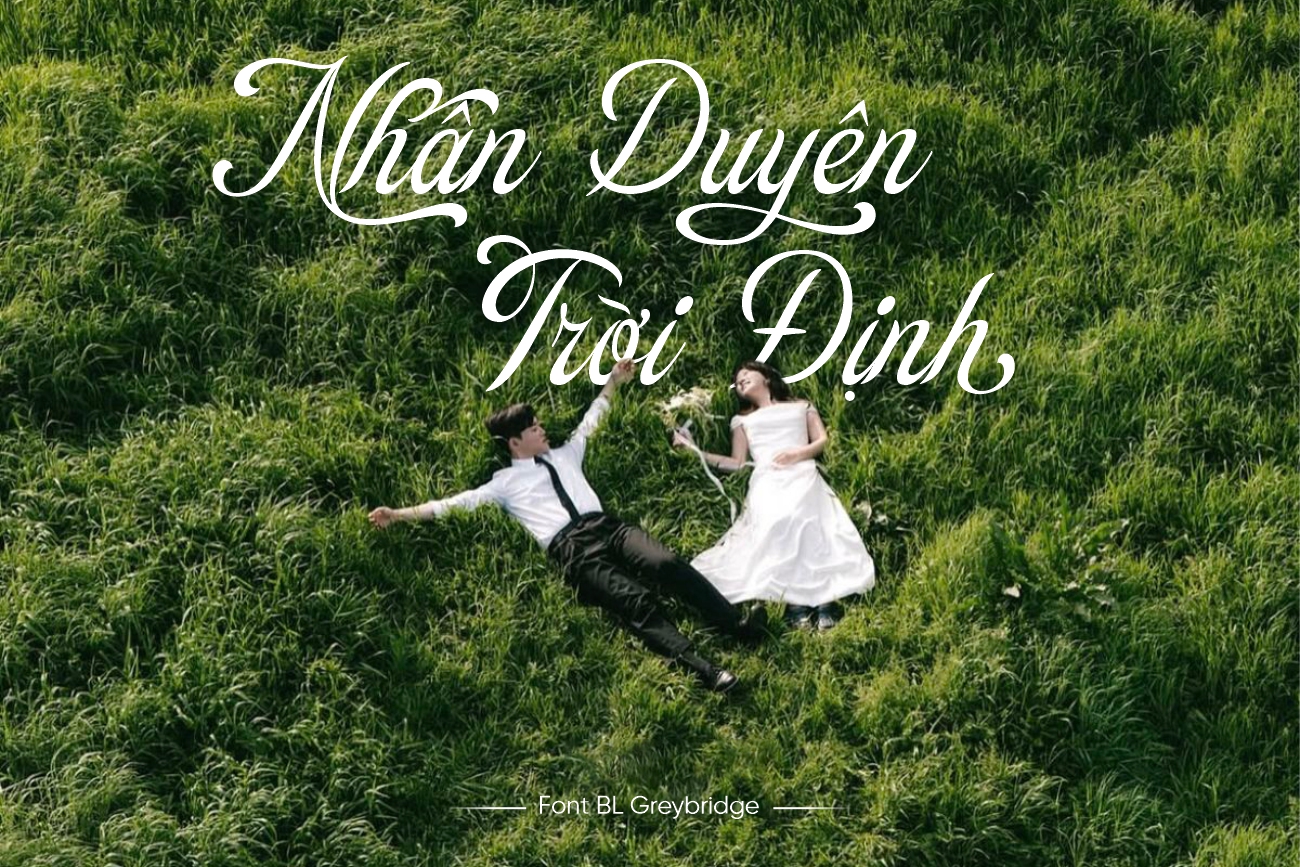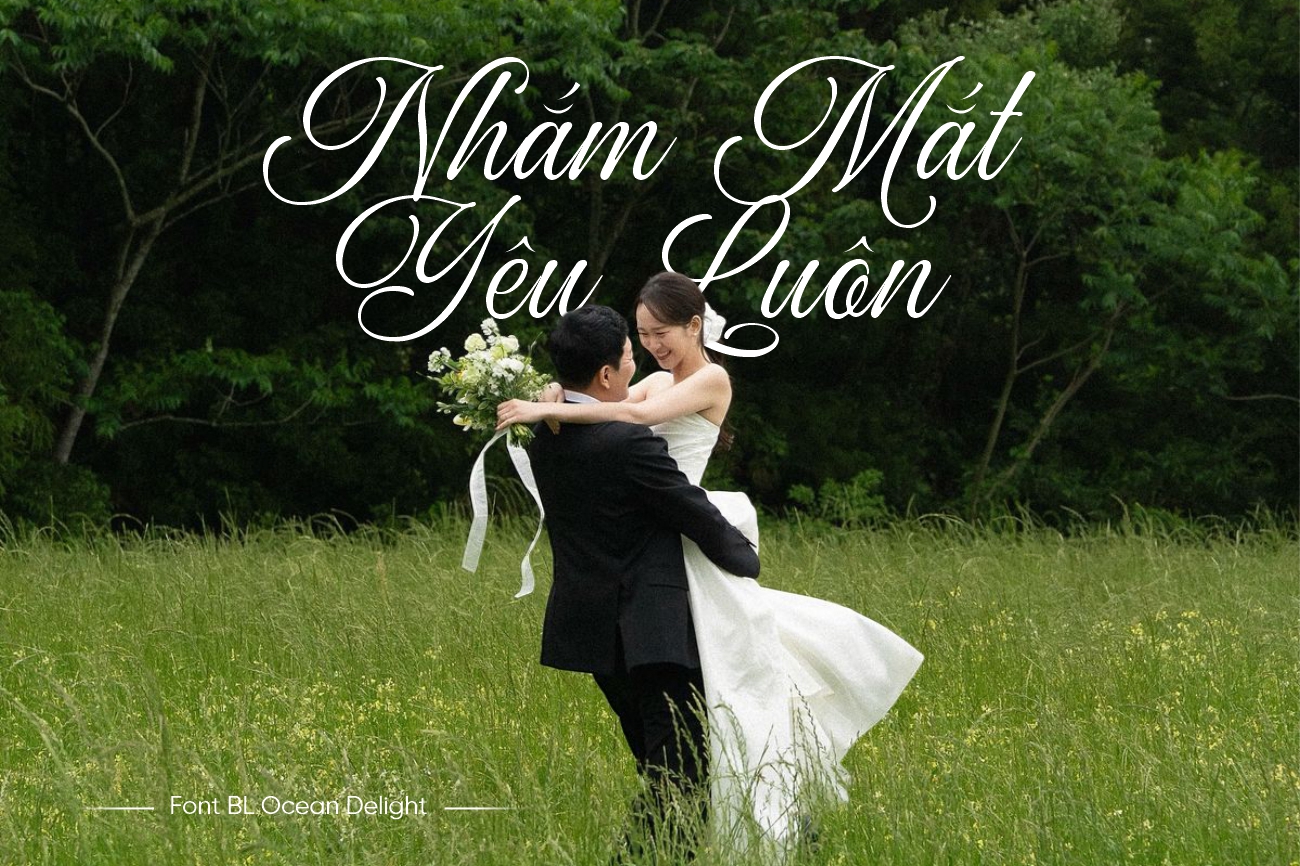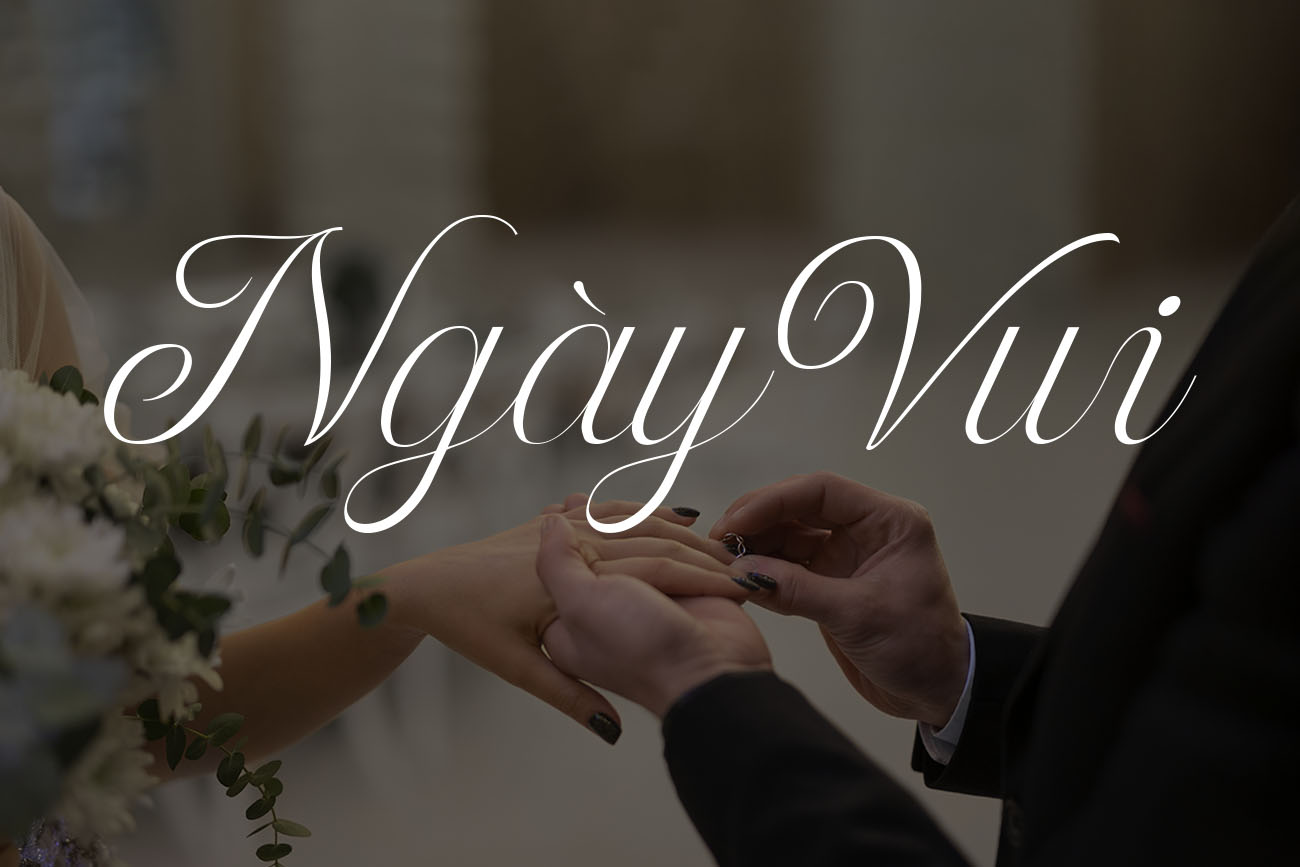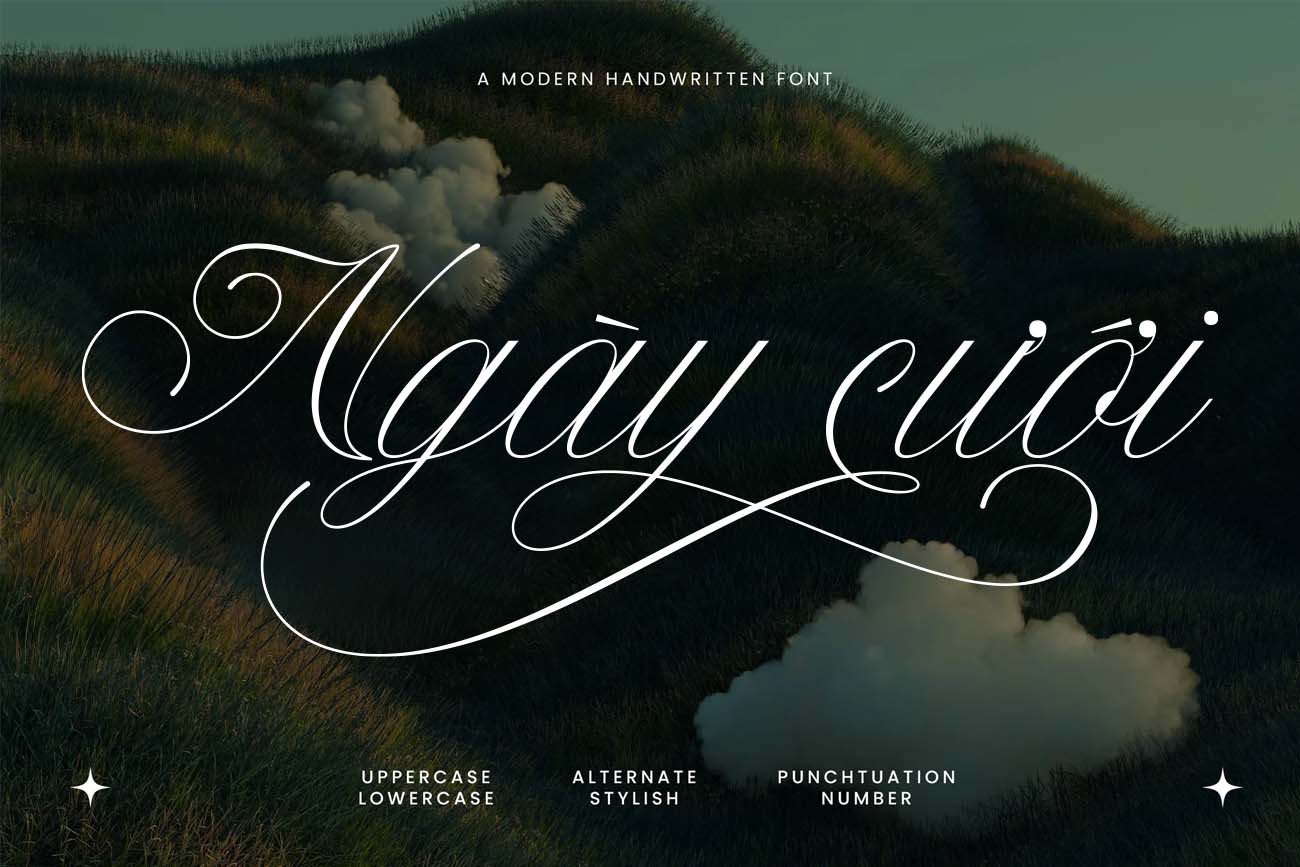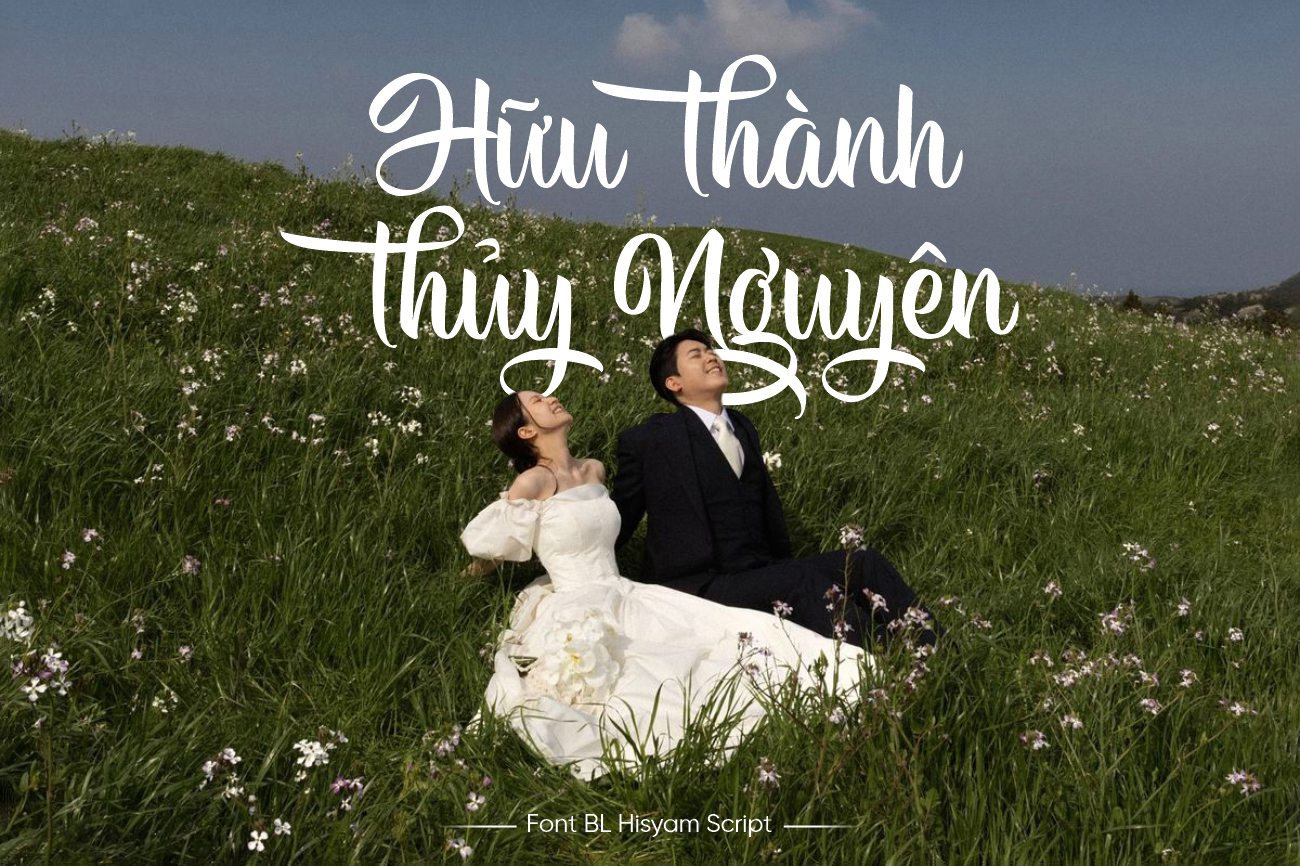
Top 20 font chữ cho album ảnh cưới, bảng welcome và backdrop tiệc cưới
Gợi ý 20 font album ảnh cưới, font bảng welcome cưới và font backdrop cưới Việt hóa đẹp, dễ ứng dụng cho studio, planner và designer.
Ảnh cưới không chỉ cần màu đẹp, layout cân đối hay khoảnh khắc tự nhiên. Phần chữ trên album, bảng welcome, backdrop sân khấu, thiệp mời, save the date hay story recap cũng quyết định rất nhiều đến cảm giác sang trọng của toàn bộ bộ nhận diện cưới. Một font quá rối có thể làm tên cô dâu chú rể khó đọc. Một font quá cứng lại khiến concept lãng mạn mất đi độ mềm. Vì vậy, chọn đúng font album ảnh cưới là bước nhỏ nhưng ảnh hưởng trực tiếp đến cảm xúc của thiết kế.
Với thiết kế cưới tại Việt Nam, font cần đáp ứng thêm một yêu cầu rất quan trọng: hiển thị tiếng Việt đẹp. Các dấu sắc, huyền, hỏi, ngã, nặng phải nằm gọn trong nhịp chữ, không bị vỡ, không chạm nét và không làm tên riêng trở nên nặng nề. Danh sách dưới đây tập trung vào các font wedding Việt hóa phù hợp cho designer, studio ảnh cưới, wedding planner, dịch vụ in ấn và các cặp đôi muốn tự làm ấn phẩm cưới.
Cách chọn font cho album ảnh cưới, bảng welcome và backdrop
Trước khi đi vào danh sách font, bạn nên chia ấn phẩm cưới thành ba nhóm chính. Mỗi nhóm sẽ cần một sắc thái chữ khác nhau.
Album ảnh cưới cần font mềm nhưng không quá khó đọc
Album ảnh cưới thường có nhiều trang, nhiều ảnh và nhiều khoảng trắng. Font dùng cho tên cặp đôi, ngày cưới hoặc một câu quote ngắn nên có nét bay vừa phải, không quá nhiều flourish. Nếu dùng font script quá phức tạp ở kích thước nhỏ, dấu tiếng Việt và các chữ như "ư", "ơ", "ă", "đ" rất dễ bị rối. Với album, hãy ưu tiên font script thanh lịch, chữ ký mềm hoặc serif tinh tế.
Bảng welcome cưới cần font nổi bật từ xa
Bảng welcome thường được đặt ở khu vực check-in, nơi khách nhìn từ khoảng cách xa hơn so với album. Vì vậy, font tên cô dâu chú rể có thể mềm mại, nhưng phần ngày tháng, địa điểm, lời chào nên dùng font dễ đọc hơn. Một công thức an toàn là script cho tên riêng, serif hoặc sans serif nhẹ cho thông tin phụ.
Backdrop tiệc cưới cần font có độ sang và đủ lực thị giác
Backdrop sân khấu hoặc photobooth có kích thước lớn, thường xuất hiện trong ảnh chụp khách mời. Font backdrop cưới nên có dáng đẹp khi phóng lớn, nét chữ không quá mảnh nếu in trên chất liệu bạt, mica, foam hoặc màn LED. Nếu concept luxury, hãy chọn calligraphy hoặc serif cao cấp. Nếu concept ngoài trời, garden party, beach wedding, có thể chọn script phóng khoáng hơn.
Top 20 font wedding Việt hóa nên dùng cho thiết kế cưới
1. TH Quadrien Script
TH Quadrien Script là lựa chọn rất hợp cho tên cô dâu chú rể trên bảng welcome, thiệp mời và trang mở đầu album cưới. Nét chữ có độ uốn mềm, tạo cảm giác trang trọng nhưng vẫn gần gũi. Font này phù hợp với concept cưới lãng mạn, studio tone sáng, ảnh pre-wedding trong vườn hoa hoặc bối cảnh châu Âu nhẹ nhàng.
Khi dùng TH Quadrien Script, bạn nên đặt tên riêng ở kích thước lớn và giữ nhiều khoảng thở xung quanh. Phần thông tin như ngày cưới, địa điểm, hashtag nên ghép cùng một font serif hoặc sans serif mảnh để tổng thể không bị quá nhiều nét lượn.
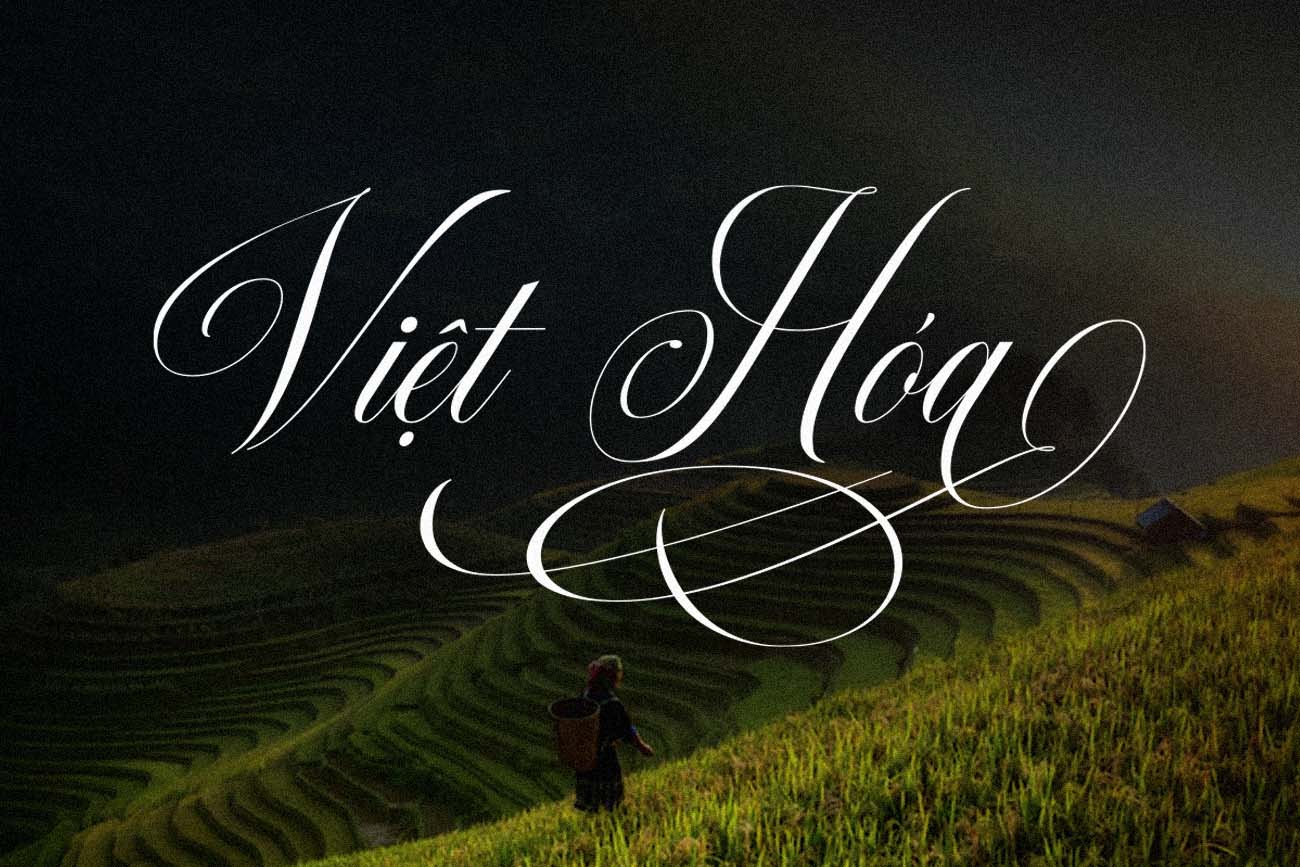
2. BL Southwester
BL Southwester mang cảm giác calligraphy cổ điển, phù hợp với thiệp cưới, bảng welcome và các layout ảnh cưới cần một điểm nhấn nghệ thuật. Nét chữ có độ bay, tạo cảm giác thủ công và tinh tế, đặc biệt đẹp khi dùng cho tên cặp đôi hoặc tiêu đề như "Wedding Day", "Save the Date", "Welcome to our wedding".
Với album ảnh cưới, BL Southwester nên được dùng tiết chế. Một câu quote ngắn hoặc tên nhân vật chính sẽ đẹp hơn là dùng cho đoạn văn dài. Font này hợp với tone ảnh ấm, concept vintage, tiệc cưới ngoài trời hoặc phong cách rustic sang trọng.
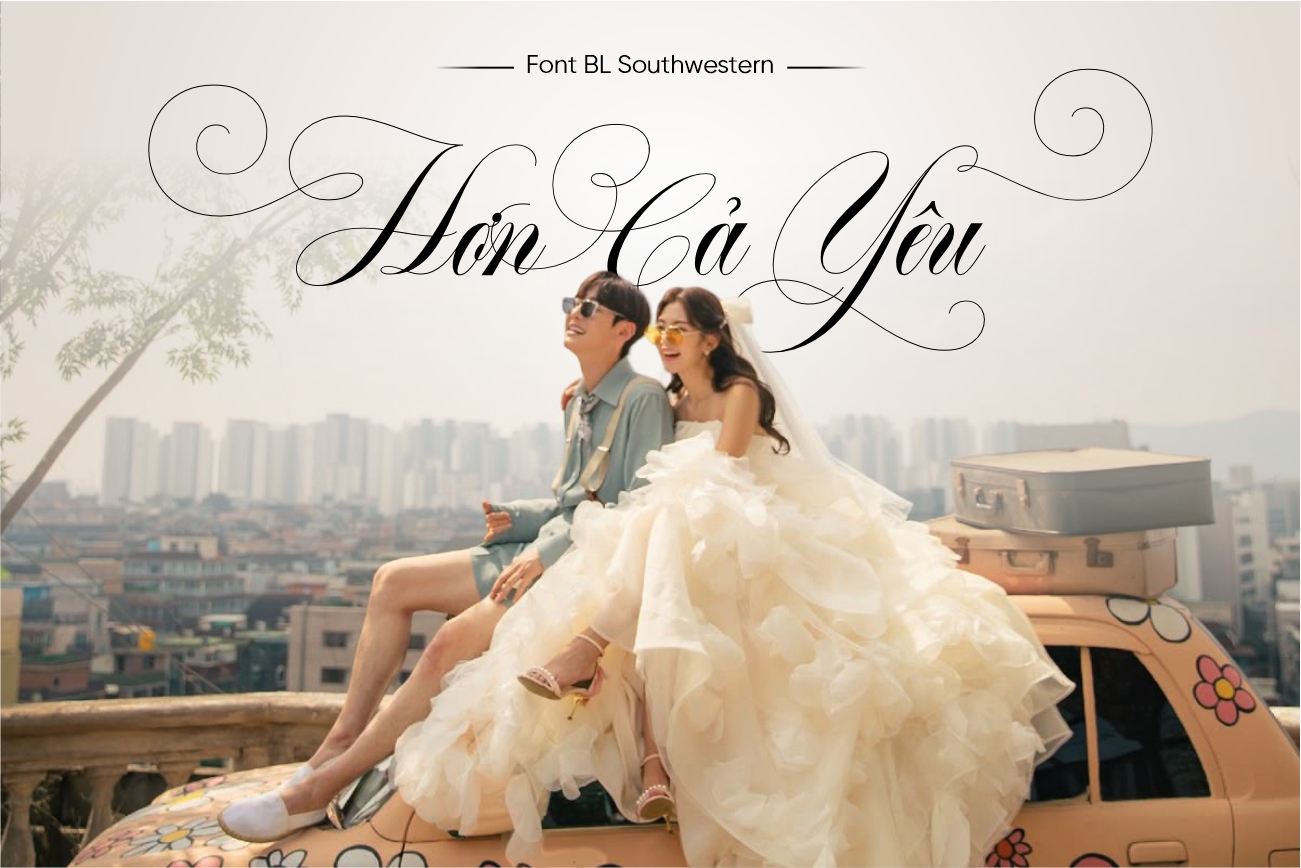
3. TH Newly Bridal
Đúng như tên gọi, TH Newly Bridal sinh ra cho các thiết kế mùa cưới. Font có tinh thần mềm, ngọt và hiện đại, thích hợp cho thiệp cưới, backdrop cưới, poster dịch vụ cưới, bảng tên bàn tiệc và ảnh bìa album. Ưu điểm của font là tạo cảm giác wedding rõ ràng mà không quá nặng tính cổ điển.
Nếu bạn cần một font backdrop cưới dễ tạo cảm xúc ngay từ cái nhìn đầu tiên, TH Newly Bridal là lựa chọn nên thử. Hãy dùng màu trắng, vàng champagne hoặc nâu nhạt trên nền ảnh tối nhẹ để tên cặp đôi nổi bật hơn.
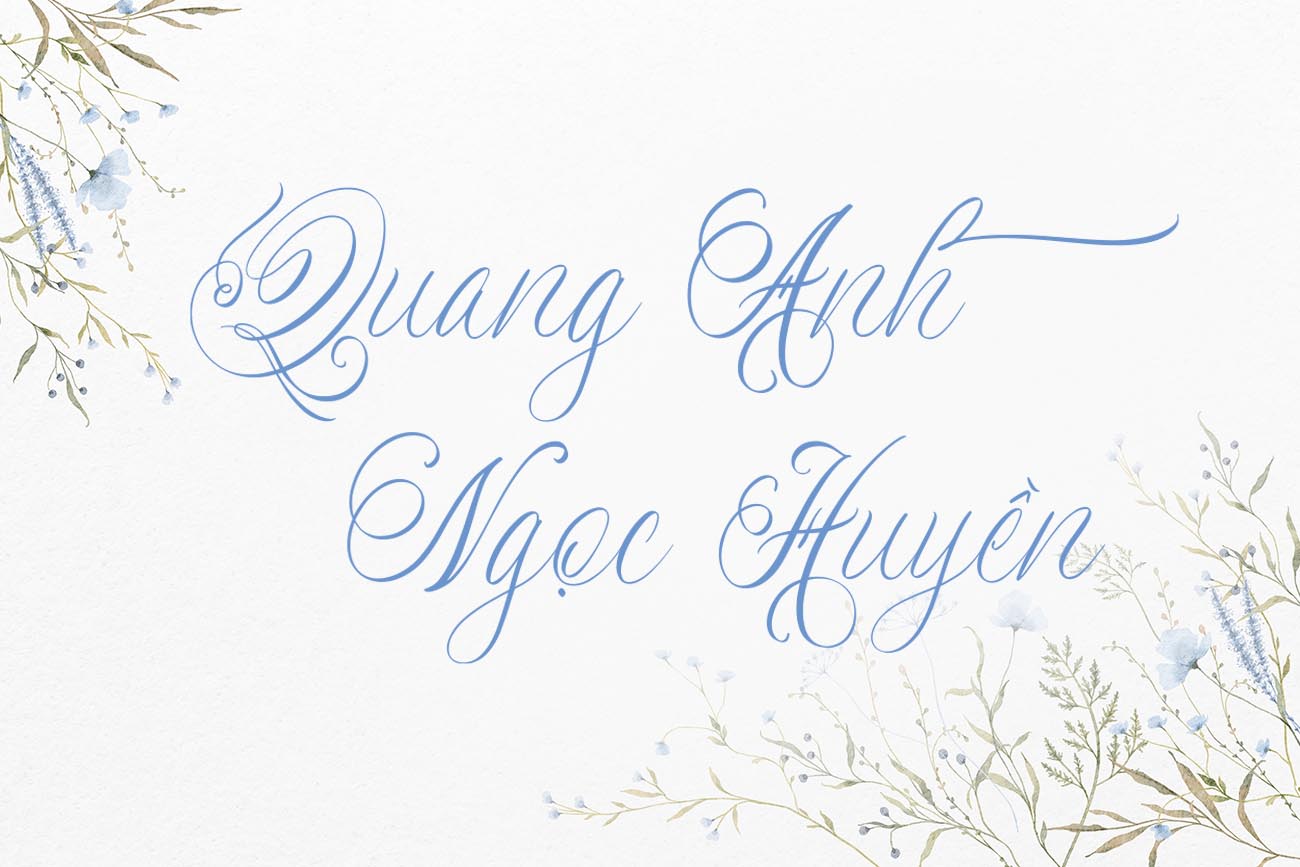
4. BL Greybridge
BL Greybridge hợp với những thiết kế cưới theo hướng classic, fine art, sang trọng và có chút hoài niệm. Nét calligraphy tạo cảm giác cao cấp, đặc biệt phù hợp cho wedding invitation, bảng welcome đặt trong khung gỗ, backdrop hoa tươi hoặc layout album có nhiều khoảng trắng.
Font này nên đi cùng bảng màu kem, xanh olive, vàng nhạt, xám ấm hoặc nâu vintage. Khi dùng trên ảnh cưới, nên chọn vùng nền ít chi tiết để nét chữ không bị lẫn vào váy cưới, hoa cưới hoặc hậu cảnh.
Bạn có thể bắt đầu từ một font chính cho tên cặp đôi, sau đó chọn thêm một font phụ thật dễ đọc cho ngày tháng, địa điểm và thông tin tiệc. Khi chữ đẹp, rõ và đúng cảm xúc, toàn bộ bộ ảnh cưới sẽ có cảm giác chuyên nghiệp hơn, từ file thiết kế trên màn hình đến sản phẩm in cầm trên tay.